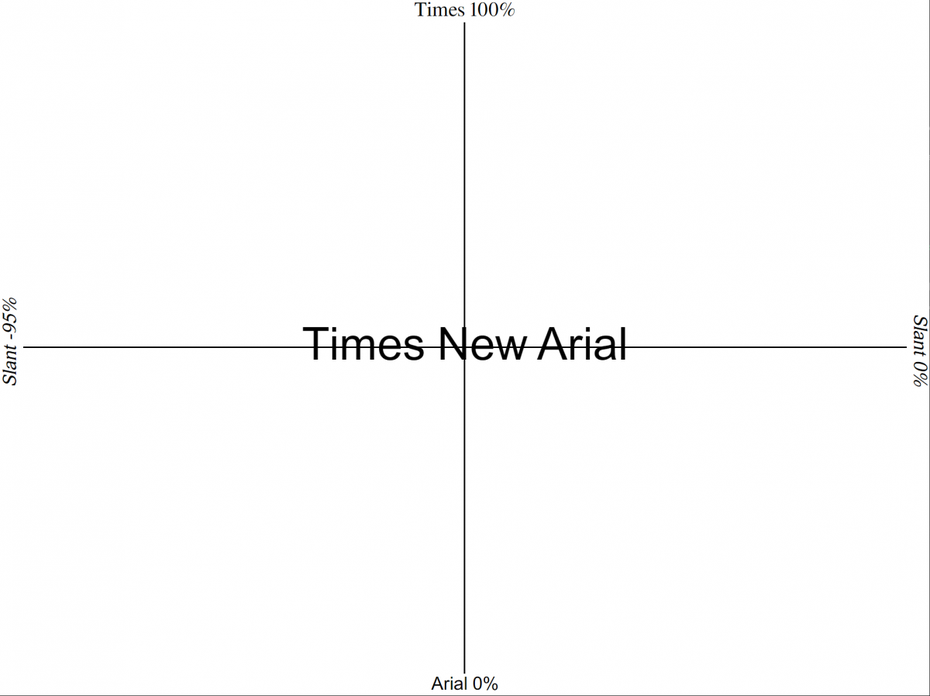
Design mit variablen Fonts: Times New Arial vereint Serifen und Serifenlose
Hamburger Designer sind auf die zunächst seltsam erscheinende Idee gekommen, die serifenlose Schrift Arial mit der Serifenschrift Times New Roman zu verbinden. Welche Schrift in welchem Maße in der Verbindung beider dominiert, kann dynamisch festgelegt werden.
Times New Roman und Arial sind mit Abstand die verbreitetsten Schriftarten inner- und außerhalb des Web. Sie sind quasi die Archetypen moderner Schriftsetzung und stellen die Gegenpole dar. Schon seit der Frühzeit digitaler Textverarbeitung werden beide Schriften mit den gängigen Betriebssystemen geliefert.
Times New Roman und Arial: Omnipräsente Fonts
Im Web der Neunziger waren sie in der Mehrzahl aller Websites im Einsatz. Das lag ganz einfach daran, dass Designer nur Schriften einsetzen konnten, die auf den Geräten der Seitenbesucher ziemlich sicher zur Verfügung stehen würden. Das war mit Times New Roman und Arial am ehesten gewährleistet.
Times New Roman ist eine Schrift mit Serifen. Serifen, auch als Beistrich bezeichnet, sind die Anfangs- und Endstriche an den Buchstaben, die auf den ersten Blick überflüssig wirken, einem Font jedoch eine besondere Optik verleihen. Zusätzlich zu den Beistrichen variieren Serifenschriften zumeist auch die Strichstärken innerhalb der Buchstaben. Schriften mit Serifen werden bevorzugt da eingesetzt, wo ein klassisches Schriftbild mit einer gewissen Eleganz und einer traditionellen Optik gewünscht wird.
Arial ist hierzu der Widerpart. Diese serifenlose Schrift verzichtet auf jeglichen Beistrich und variiert auch die Strichstärken innerhalb der diversen Zeichen nicht. Serifenlose Schriften werden gemeinhin als modern und nüchtern wahrgenommen.
Designer kreuzen Times New Roman und Arial in einer variablen Schrift
Die Hamburger Designer von Liebermann Kiepe Reddermann haben nun die beiden Schriften genommen und daraus einen sogenannten variablen Font gemacht.
Das geht seit einigen Jahren, nämlich seit der Einführung der Open-Type-Spezifikation in Version 1.8 im September 2016. Damit ist es unter Nutzung von CSS möglich, Schriften abhängig von verschiedensten Bedingungen zu dynamisieren. Bei variablen Fonts benötigen Designer nicht mehr mehrere Webfont-Varianten derselben Schriftart, sondern lediglich eine.
Im Falle von Times New Arial erfolgt die Dynamisierung über die Steuerung der Anteile der Merkmale der jeweiligen Ausgangsschrift am Endformat. Klingt kompliziert, ist es aber nicht. Spielt selber mal mit diesem Simulator herum.
Mit diesem Tool könnt ihr die mögliche Dynamisierung einmal selbst durchspielen. (Screenshot: t3n)
Neben der Möglichkeit, festzulegen, welche Font-Anteile in der optischen Wahrnehmung dominieren sollen, besteht zusätzlich die Option, eine Schrägung anzugeben. Schrägung deshalb, weil es kein echtes Kursiv, sondern lediglich eine prozentuale Neigung der Ausgangsschrift ist.